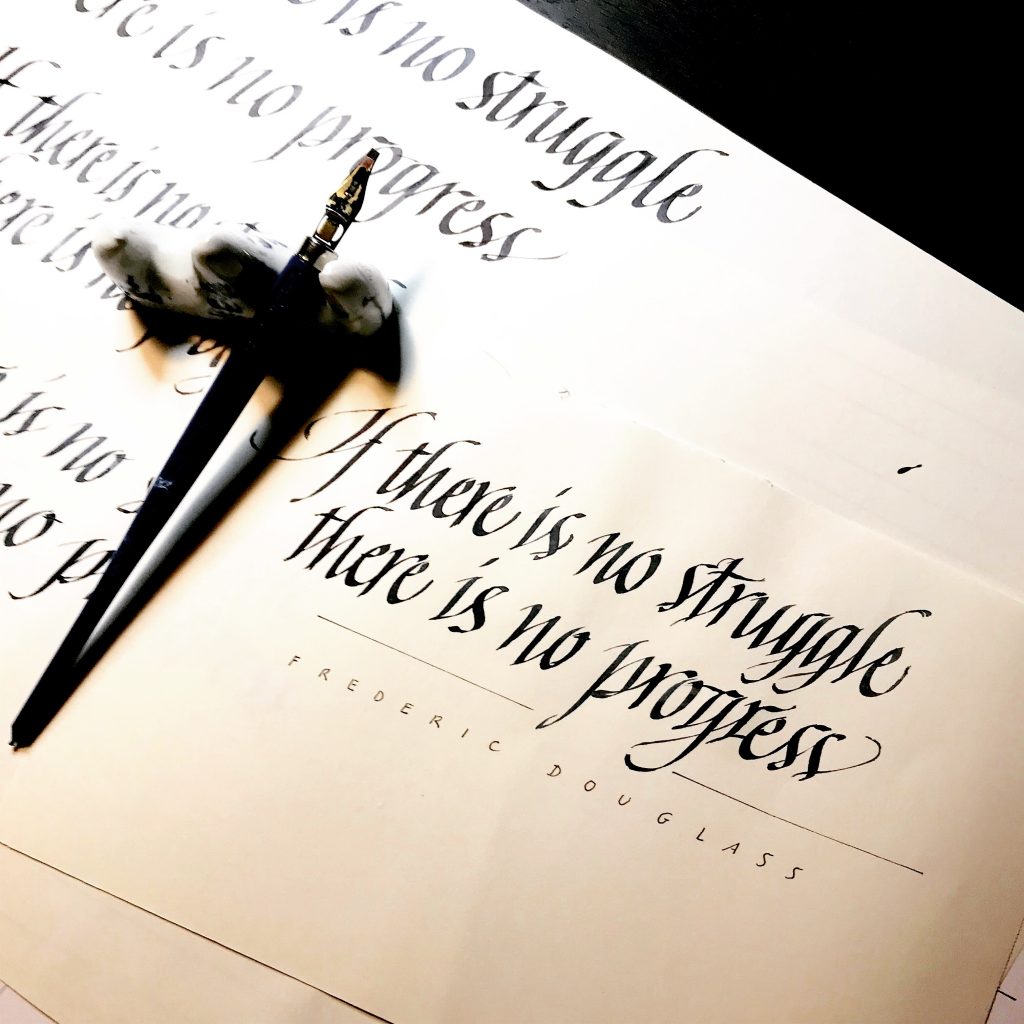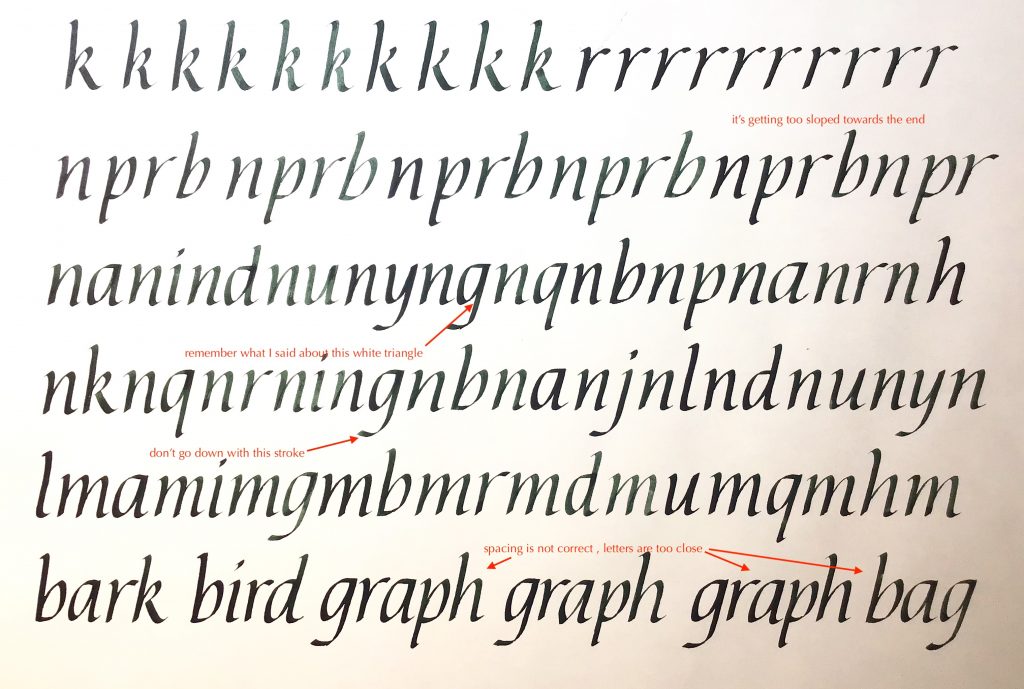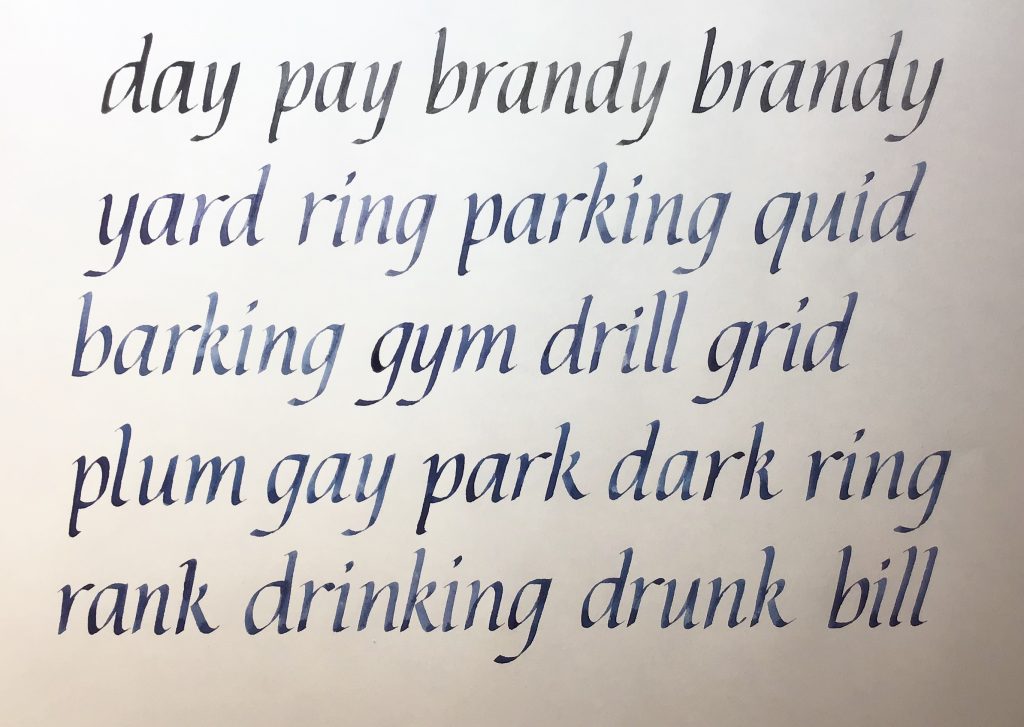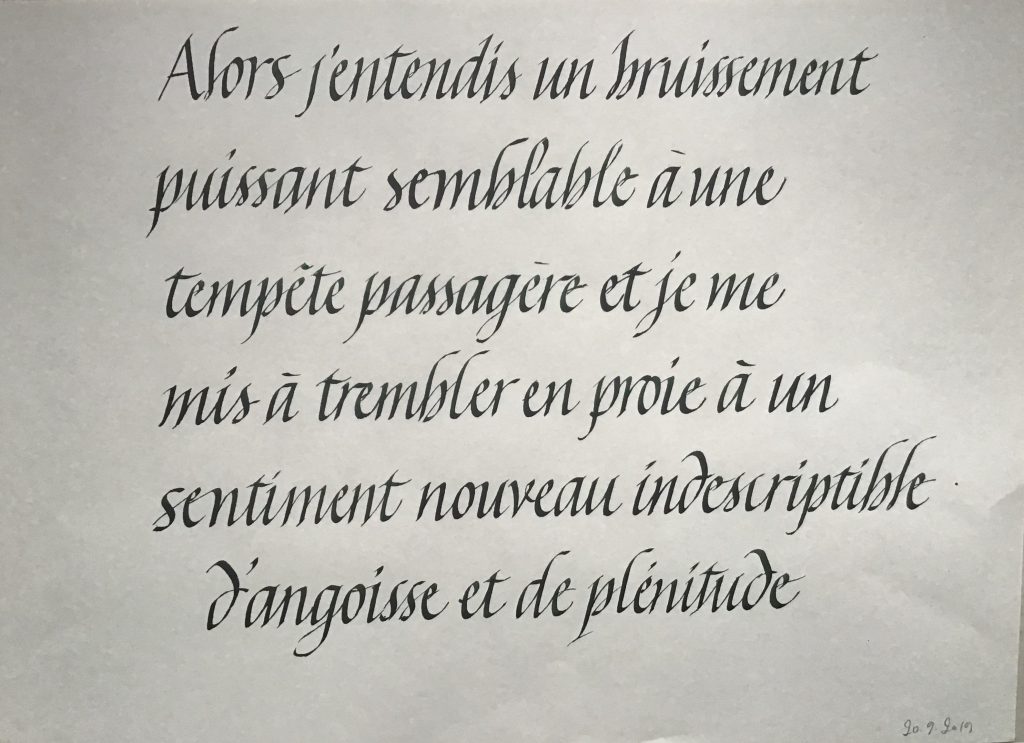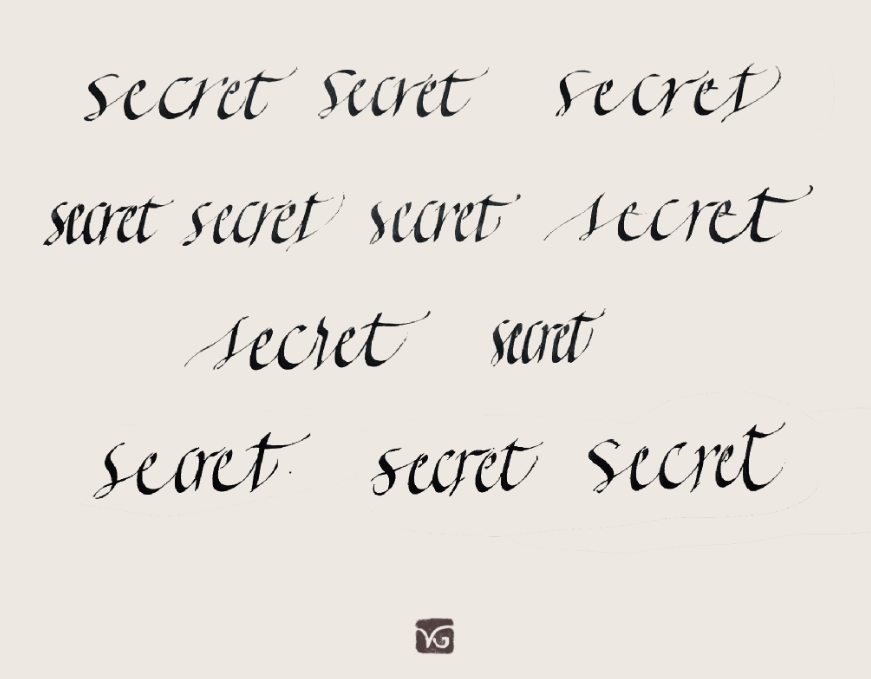
Petit flashback sur ce qui a occupé mon retour de congés d’été : le stage de Chancelière en ligne d’Yves Leterme.
La Chancelière est une écriture que j’ai peu pratiquée… Enfin, ce n’est pas totalement vrai : disons que nous nous sommes rencontrées plusieurs fois, mais sans grand succès. J’ai en effet réalisé mes premiers essais il y a une dizaine d’années, en autodidacte, armée du livre de David Harris et du Mediavilla, et c’était absolument horrible. Ensuite, je l’ai pratiquée comme ci comme ça, en étant toujours très frustrée par le résultat. Malgré divers stages je n’avais toujours pas le sentiment d’avoir dompté la belle italienne et d’en avoir saisi toutes les subtilités. Pour être honnête, je la trouvais ennuyeuse à réaliser dans sa forme la plus « formelle ». Mais dans le même temps, j’ai toujours eu envie de la réussir, car bien maîtrisée, c’est une écriture d’une grande finesse et très élégante. Mais voilà, je n’avais pas capté l’essentiel.
Lorsque Yves Leterme, éminent calligraphe basé dans la belle ville de Bruges, a proposé un stage en ligne de 6 semaines sur la Chancelière, j’ai longuement hésité avant de m’inscrire. En effet, les échos que j’avais eu sur le stage qu’il avait proposé sur la capitale romaine, étaient qu’il fallait énormément travailler et s’investir. Mais poussée par le fait que des amis calligraphes participaient j’ai franchi le pas, et cela a été une véritable révélation.
Qu’est-ce que la Chancelière ?
Ah oui… Revenons au début. La chancelière est une écriture italienne de la renaissance, réservée à l’origine pour la chancellerie papale, d’où son nom. Née de l’écriture humanistique, souple et élancée, elle rompt avec le côté rigide et carré des écritures gothiques alors largement usitées. Sobre et nette dans ses premières apparitions, elle sera ensuite enjolivée d’arabesques et sujette à de nombreuses variations, jusqu’à la gestuelle.
On l’aime car elle est moderne, élancée et élégante.
C’est une écriture assez difficile, qui demande beaucoup d’heures de pratique et d’observation. D’ailleurs, si quelqu’un vous dit « Je suis calligraphe », demandez-lui de vous montrer ses pages de Chancelière ! En effet, elle fait partie de ces écritures qui ne trichent pas : mal exécutée, c’est vraiment la misère. Maîtrisée, c’est un bonbon pour les yeux.
Nouveau départ : retour à la base de l’écriture
Les deux premières semaines du stage en ligne « Thoughtful Gesture » d’Yves Leterme ont été consacrées à la reprise en main de la Chancelière dans sa forme la plus simple, avec un ductus très formel.
Astuce pour travailler l’espacement : alternance de « n » avec les autres lettres de l’alphabet
Nous avons travaillé avec des plumes Speedball C2, donc sur un grand module de 1.5cm, et avons repris les bases lettre par lettre. Rien que ce travail, guidé par les explications d’Yves et ses démonstrations, a été très bénéfique.
Ce qui est difficile, dans la Chancelière formelle, c’est vraiment de rester léger, tout en étant très rigoureux sur l’inclinaison, l’angle de la plume à 45°, l’espacement judicieux des lettres et l’analyse des contre-formes. Pour y arriver, pas de secret : des pages et des pages d’entraînement. Mais grâce aux explications d’Yves, à sa pédagogie, j’ai pris beaucoup de plaisir là où auparavant je m’ennuyais assez vite.
Comme toujours je peine à rester légère. Pour limiter le trop de pression sur la main qui écrit, je tiens un gros Posca dans la main gauche, que je broie allègrement. Cela déporte la crispation sur la main qui n’écrit pas, et ça marche plutôt bien.
Travail sur les liaisons et les variations de formes
Après avoir étudié le modèle très formel, place aux variations en introduisant des liaisons entre les lettres et de légères variations de formes. Yves nous a fait travailler sur ces différents paramètres, tout en restant dans le contrôle total. Chaque geste est bien réfléchi et on se rend compte qu’on a mille décisions à prendre à chaque étape. C’est costaud au début, mais au fil des pages, on acquière plus d’aisance et d’automatismes dans les enchaînements.
Premier jet dans un ductus formel
Deuxième jet avec un travail plus recherché sur les formes et les liaisons
En route vers la gestuelle
Progressivement, on casse le côté bien rangé, bien propret. Mais là encore, les variations qui sont introduites le sont avec beaucoup de subtilité. On introduit des variations de hauteur, on comprime les lettres, tout en continuant d’utiliser ce que l’on a appris sur les liaisons et les variations de formes.
Cela fait beaucoup de paramètres à avoir en tête : immanquablement, cela génère beaucoup de ratés. L’entraînement sur un mot, une petite phrase que l’on répète 3, 4 voire 10 fois font énormément avancer.
Variations sur un mot : exploration des diverses possibilités
A ce stade du stage, j’avoue que j’ai calé. Difficile de passer à la suite – la gestuelle – alors que j’avais encore tellement à travailler sur les premières leçons. Mais ce n’est pas grave, j’y reviendrai plus tard.